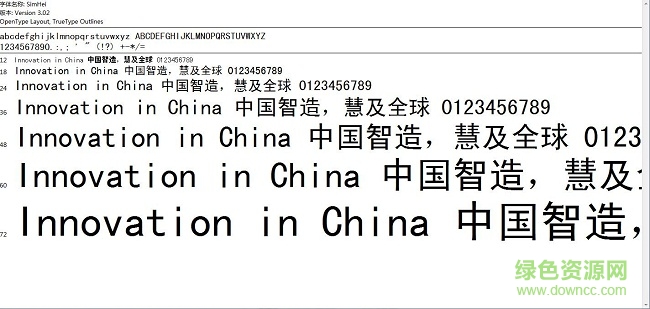
黑體-普通(western)
黑體普通西方是哪個(gè)?黑體-普通(西方)字體就是simhei.ttf字體,該字體造型規(guī)整,簡潔大氣,網(wǎng)頁設(shè)計(jì)、平面設(shè)計(jì)、書刊雜志等領(lǐng)域都可以使用,歡迎有需要者免費(fèi)下載!
黑體字體設(shè)計(jì)要點(diǎn)
黑體的各個(gè)筆劃寬度雖是大致相等,但不是絕對的,在處理上不能強(qiáng)求一律,否則筆劃多的字必然擁塞寫不下,筆劃少的則顯得空,所以應(yīng)在長與短、橫與豎、筆劃粗與細(xì)之間,作適當(dāng)?shù)恼{(diào)整,達(dá)到整體上的均勻諧調(diào)。
黑體普通(western)